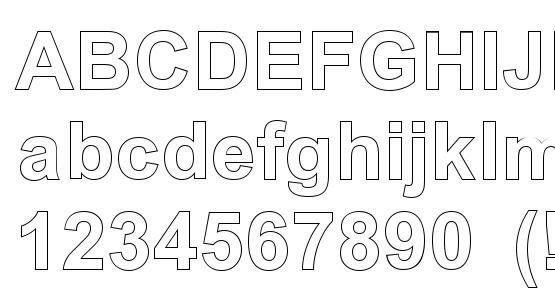
Если вы работаете над дизайном плаката, флаера или поздравительной открытки, контурный шрифт является отличным выбором для добавления заголовков, которые привлекают внимание.
В отличие от большинства других типов шрифтов, контурный шрифт легко узнаваем. Как следует из названия, контурный шрифт состоит только из контуров без заливки. Эти шрифты широко используются для создания привлекательных заголовков. Они также используются в дизайне логотипов и канцелярских товаров.
Эта коллекция включает в себя смешанную коллекцию контурных шрифтов, которые вы можете использовать в различных видах профессионального, декоративного и делового графического дизайна. Посмотрите, сможете ли вы найти контурный шрифт, который подходит вашему проекту.
VISIA Duo
Visia Duo геометрический контурный шрифт позволяет легко комбинировать и создавать уникальные дизайны.
Playbook – Creative Font Family
Если вы работаете над забавным и игривым дизайном, таким как обложка для детской книги, плакат или какой-либо другой дизайн, связанный с детьми, этот креативный контурный шрифт пригодится вам. Шрифт представлен в виде набросков, заливки и обычных стилей, что позволяет создавать привлекательные заголовки и заголовки для различных дизайнов.
Zeuty Font
Zeuty Font — коллекция современных винтажных шрифтов поставляется с 4 различными шрифтами, включая контурный шрифт, скрипт-шрифт, обычный и swash. Все шрифты отличаются современным дизайном, вдохновленным винтажной типографикой. Возможность выбора из более чем одного дизайна позволит вам использовать этот пакет шрифтов с вашими различными дизайнерскими проектами.
Pittsbrook
Обладая дизайном, вдохновленным классическим дизайном шрифтов, используемых в винтажной упаковке, этот контурный шрифт разработан специально для создания этикеток и заголовков.
Тем не менее, шрифт также выглядит как отличный выбор для разработки логотипов, связанных со спортом.
Fuera
Несмотря на то, что это не контурный шрифт, Fuera поставляется с креативным дизайном, который мы не могли удержать, в том числе и в нашем списке. Этот шрифт имеет стильный дизайн Duoline, что делает его похожим на контурный шрифт. Шрифт включает два стиля шрифтов наряду с курсивом.
Polygon Technology
Несмотря на то, что это технически не контурный шрифт, его уникальный дизайн делает его достойным места в нашем списке. Polygon Technology – футуристический шрифт имеет полую форму, похожую на контур, созданную в форме многоугольника. Это идеально подходит для разработки уникальных названий и логотипов.
Monday Vacation
Monday Vacation — это пара уникальных шрифтов. Он включает в себя шрифт кисти и контурный шрифт без засечек, которые хорошо сочетаются в различных креативных проектах. Это бесплатно для личных проектов.
Library 3 AM
Library 3AM — это бесплатный контурный шрифт с креативным дизайном. Этот шрифт идеально подходит для создания логотипов, визиток, плакатов и многого другого. Шрифт можно использовать бесплатно в личных и коммерческих проектах.
Portico Outline
Ищете контурный шрифт для оформления больших жирных заголовков и заголовков? Смотрите не дальше. Схема Portico Outline включает в себя все элементы, необходимые для создания привлекательных заголовков, плакатов и баннеров, которые привлекают внимание. В сочетании с обычной версией шрифта Portico, он делает отличный выбор шрифтов для многих типов дизайнов.
Gibsons
Gibsons — это семейство шрифтов с классическим и винтажным дизайном. Он включает в себя несколько стилей шрифтов, таких как контурный, обычный и жирный. Этот шрифт идеально подходит для создания этикеток в винтажном стиле, особенно для брендов напитков и алкоголя.
Hikou
Бренды моды и одежды также часто используют контурные шрифты для создания смелых заголовков и привлекательных фирменных дизайнов.
Этот шрифт имеет уникальный дизайн, созданный специально для этих целей. Согласно дизайну, шрифт выглядит более привлекательно при использовании неоновых цветов.
Darling Bloom
Этот красивый контурный шрифт обладает уникальным женским дизайном, что делает его отличным выбором для создания логотипов, поздравительных открыток, приглашений и многого другого. Уникальный дизайн персонажей шрифта, безусловно, выделит ваши дизайны из толпы.
Fairytales
Милый и очаровательный контурный шрифт с женским стилем дизайна. Этот шрифт обладает своей уникальной индивидуальностью, которая позволит вам создавать более привлекательные и увлекательные дизайны, независимо от того, печатные они или цифровые.
Elephant Outline
Elephant — это семейство из 6 шрифтов, которые включают в себя различные стили шрифтов, начиная от набросков и заканчивая грубыми текстурами и многим другим. Все шрифты могут свободно использовать с вашими личными проектами.
Burford Outline
Это набросок популярного семейства шрифтов Burford. Он отличается таким же смелым и элегантным дизайном, как и его предшественники. Вы также можете скачать все остальные шрифты из семейства Burford из Envato Elements.
Важной особенностью курсива является требование его «оживления» в процессе вывода на устройства отображения (дисплей или принтер).Под возрождением понимаются небольшие вариации шрифта отдельных персонажей, присущие настоящему почерку любого человека. Эти вариации выражаются в небольших изменениях ширины и формы штрихов для одних и тех же знаков. С точки зрения такого «возрождения» существующие решения по созданию контурных рукописных шрифтов обладают рядом недостатков. Прежде всего, контурное описание шрифта не позволяет реализовать вариации ширины штриха и формы пера. Описание контура требует решения сложной задачи синхронного изменения обеих границ штриха.Во-вторых, в процессе вариации хода необходимо обеспечить сохранение гладкости контура там, где это необходимо. Автоматическое поддержание гладкости составных кривых Безье также является нетривиальной задачей. Изображение курсива с помощью модели следа пера «по ширине» (рис. 2) потенциально дает больше возможностей для создания персонального «компьютерного почерка».